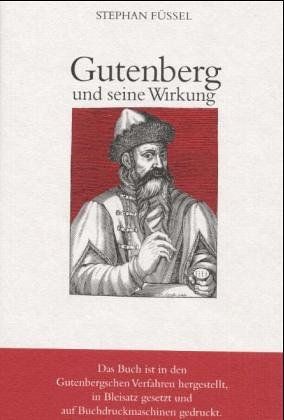
Stephan Füssel: Gutenberg und seine Wirkung.
Eine wissenschaftlich gesicherte Biographie und eine Wirkungsgeschichte des soeben zum 'Mann des Jahrtausends' gewählten Mainzer Erfinders. Neben der Beschreibung seiner Lebensstationen in Straßburg und Mainz und seiner technischen Leistungen, der Entwicklung des Buchdrucks, vom Guß der Typen über den Satz bis zum Druckverfahren selbst, steht die unvergleichliche Erfolgsgeschichte der Ausbreitung der 'Schwarzen Kunst' in nur 40 Jahren quer durch Europa.